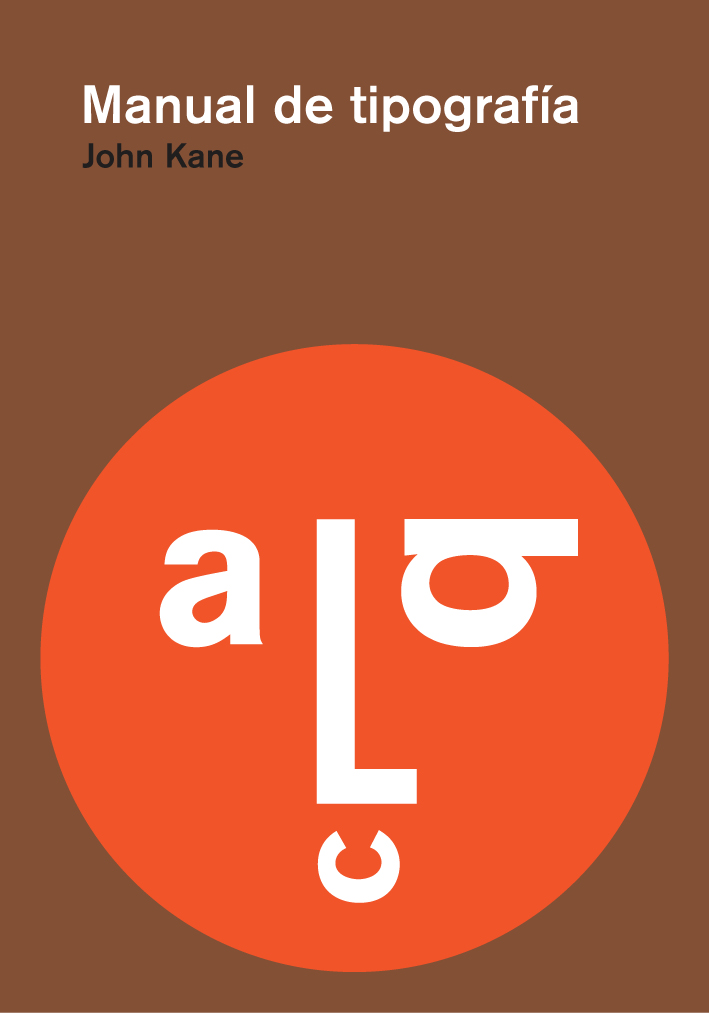
Manual de tipografía
Un libro de John Kane
Este libro constituye una práctica introducción a la tipografía donde se abordan sus principios básicos y sus distintas
aplicaciones. El autor analiza todo lo que el estudiante que
inicia sus estudios de diseño gráfico precisa conocer acerca de la tipografía: desde la clasificación de las diferentes tipografías a la disposición del texto en la página y el
funcionamiento de los sistemas de retículas. Además, incluye una breve historia de la tipografía, numerosos ejemplos que ilustran las cuestiones desarrolladas a lo largo del libro y una serie de ejercicios prácticos que sirven de ayuda al lector.
Índice de contenidos: Agradecimientos Presentación Conocimientos básicos Describir las partes de la letra La fuente Describir los tipos Medir la tipografía Comparar los tipos Desarrollo Una línea temporal Clasificación de las tipografías de texto Letras Comprender las formas de letras Mantener la altura de x Forma y contraforma Contraste Palabras y frases Reforzar el significado Crear oraciones, encontrar el sentido El español no es chino Texto El tracking: el kerning y el interletrado Composición de textos Textura No es lo mismo mecanografía que composición tipográfica El interlineado y la longitud de línea Un libro de muestras de tipo Indicar los párrafos Líneas viudas y huérfanas Destacar textos Titulares dentro del texto Alineaciones cruzadas Una organización sencilla Tipos de proporciones Ubicación del texto en la página Expresarse con jerarquías tipográficas Información tabulada Sistemas de retículas Introducción Un ejemplo Componentes de la retícula Una retícula sencilla Crear una retícula para texto e imágenes Conclusiones Apéndices y bibliografía Apéndice A: disposición de las letras en el teclado Macintosh Apéndice B: 20 tipos Selección de bibliografía Índice de términos |
Presentación: Diseñar es resolver problemas. El diseño gráfico consiste en resolver problemas creando signos. La tipografía es un conjunto de signos especialmente rico, porque consigue que el lenguaje sea visible. Manejar la tipografía de forma efectiva es esencial para un diseño gráfico efectivo. Dicho esto, puedo afirmar que este es un libro práctico. Durante más o menos los últimos veinte años que he dedicado a enseñar tipografía, he sido incapaz de encontrar un solo texto que les explicase con claridad a los estudiantes principiantes la compleja conjunción de mensaje, imagen e historia que conforma la tipografía. Algunos de los mejores textos sobre historia carecen de ejemplos suficientes; algunos de los mejores textos teóricos se dirigen más a los profesionales que a los novatos. Y no hay ningún texto que ofrezca a los estudiantes los datos fundamentales según una secuencia que refuerce los ejercicios básicos que se realizan en cualquier curso introductorio. Lo que pretendo con este libro es presentar los principios básicos y las aplicaciones tipográficas de un modo que refleje lo que ocurre en el aula, y corroborar esa información con una serie de ejercicios que consoliden los conocimientos adquiridos. Mi intención es acompañarte a ti, estudiante principiante de diseño gráfico, hasta el punto en el que puedas comprender y demostrar los principios básicos de la tipografía. Si el instinto es la suma del conocimiento y la experiencia, este libro constituye un intento de ampliar ambas cosas con el fin de reforzar tus propias intuiciones tipográficas. También debería señalar que este es un libro para autodidactas. Lo que yo sé sobre tipografía lo aprendí a base de lectura, práctica y observación. Fui lo bastante afortunado al leer a Emil Ruder en primer lugar. Y también lo fui por poder trabajar en Boston en una época en la que había docenas de profesionales de gran talento que estaban intentando resolver los mismos problemas a los que yo me enfrentaba cotidianamente, a medida que todos íbamos pasando desde la tipografía de plomo hacia la tipografía digital de nuestros Macs, pasando por la fase intermedia de la tipografía de fotocomposición. Lo que aprendí de todo este proceso fue la aplicación constante de la teoría a la práctica, el firme respeto hacia las letras y una búsqueda incesante de esos momentos en los que lo personal se unía —o por lo menos se acercaba— a lo platónico. Paul Rand escribió en una ocasión: 'La tipografía es un arte. La buena tipografía es Arte'. Y aquí radica el problema tanto de los profesores como de los alumnos. El oficio puede enseñarse. El arte está dentro de cada persona. Para muchos estudiantes que empiezan con la tipografía, el hecho de que no haya reglas seguras, ni exista un camino infalible para llegar al éxito, resulta frustrante. La dificultad pedagógica reside en que la tipografía es un sistema de principios basado en la experiencia, y esos principios siguen evolucionando a medida que evolucionan el lenguaje y los medios de comunicación. En innumerables ocasiones los estudiantes han preguntado: '¿Es esto correcto?', cuando de hecho no existe 'lo correcto' en tipografía. La cuestión que deberían plantearse es: '¿Funciona esto? ¿Es útil?' Los diseñadores utilizan la tipografía como reacción; como reacción a un mensaje, a un público, a un medio. La única forma de reconocer la tipografía que funciona bien es a través de una observación directa e informada. Hace falta tiempo, y hacen falta ensayos y errores para saber qué es lo que funciona, y para no preocuparse por lo que pueda ser 'correcto' o no. Cuando hayas terminado los ejercicios de este libro, deberías tener ya la experiencia suficiente como para poner a prueba tus propias ideas en relación con el uso de la tipografía. Al fin y al cabo, lo que cualquier diseñador aporta a un proyecto —la suma de lo que sabe y siente, su experiencia personal y única— es lo que garantiza que la variedad, la emoción y, ocasionalmente, la excelencia continuarán animando el diseño tipográfico. Este libro no trata sobre el estilo —una expresión característica de la actitud—, sino más bien sobre una forma clara y nítida de pensar y de hacer. El estilo pertenece al individuo; disfrutar pensando y haciendo es una sensación que todos pueden compartir. Las actitudes que han impulsado la mayor parte de las páginas que siguen son las mismas que han animado la mayor parte del arte en el siglo xx: El contenido dicta la forma. Más es menos. Dios está en los detalles. Estos tres dogmas identifican claramente el trabajo del tipógrafo: la expresión clara y apropiada del mensaje del autor, la economía de medios inteligente y un entendimiento profundo del oficio. La idea fundamental que subyace en este libro es el resultado de dos observaciones muy sencillas. En primer lugar, la tipografía es física. Hasta no hace mucho, cualquier formación en tipografía necesariamente comenzaba con la composición manual de tipos de metal. Sigue sin haber ningún modo mejor que este para comprender la absoluta fisicidad de la letra, su 'cosedad'. Cada día que pasa, sin embargo, resulta más imposible trabajar con tipos de metal. Para acercarse a la experiencia de manejar manualmente los tipos, se incluyen en este libro algunos ejercicios que exigen la representación cuidadosa de las letras. (He propuesto estos ejercicios sobre todo para los lectores que, como yo, carecen de las ventajas de una experiencia en las aulas. No se pretende que estos ejercicios sustituyan el trabajo con un buen profesor pero, desde luego, yo espero que puedan potenciar el aprendizaje también en ese caso). Estos ejercicios te ayudarán no sólo a afinar la coordinación entre tu mano y tu ojo, sino también a desarrollar cierta sensibilidad tipográfica. No puedes alcanzar esta sensibilidad solamente mirando y pensando. La única forma de valorar la realidad de la tipografía es interiorizarla. Para algunos de los ejercicios iniciales, la mejor técnica consiste en trabajar con una buena fotocopiadora. Además de proporcionar copias rápidas y claras, así como ampliaciones y reducciones razonablemente fiables, también te permite trabajar con las letras dentro de un marco, un eco débil pero audible de la fundición de moldes en un lingote de plomo. La segunda observación, sobre todo en términos tipográficos, es que la tipografía ha evolucionado a partir de la escritura manual. Si bien puede hacerse toda clase de cosas con la tipografía de un texto (en especial con un ordenador), tu trabajo logrará el mayor grado de integridad cuando lo que hagas refleje el mismo impulso que nos lleva a todos a ponernos a escribir: la comunicación efectiva, directa y útil. He adoptado la perspectiva, sobre todo en los ejercicios finales, de que las personas que usan este libro se mueven con familiaridad en el ámbito de los programas Adobe Illustrator y Quark Xpress o Adobe InDesign. También deberías disponer de por lo menos una fuente de cada una de las clasificaciones que se describen en las páginas 47-49; de hecho, no estaría mal que escogieses las diez tipografías que se destacan en la página 12. Estas tipografías ofrecen un fundamento sólido como una roca para cualquier clase de problemas relacionados con el diseño tipográfico que el futuro te pueda deparar. He utilizado numerosos ejemplos con el fin de demostrar los puntos que planteo, porque una de las cosas agradables de trabajar con tipografía es que se puede ver de forma inmediata si algo funciona o no (por esa misma razón, he tratado de reducir el texto a su mínima expresión). He diseñado prácticamente todos los ejemplos para que fuesen lo mas sencillos posible. Y esto por dos razones: en primer lugar, porque lo 'sencillo' es engañosamente difícil (y en el ámbito de la tipografía es, con frecuencia, lo deseable); y en segundo lugar, porque, como ya he dicho antes, este libro versa sobre la intención y el contenido, no sobre los efectos o el estilo. Finalmente, tal como sugiere el título, este libro solamente es un principio. Sus páginas describen, como máximo, una serie de pequeños pasos que conducen al desarrollo de una sensibilidad tipográfica bien fundamentada. Más allá de esto, tienes que observar a tu alrededor. Cada vez que veas una manifestación del lenguaje, estarás observando tipografía. Pon a prueba lo que haces en relación con lo que hacen otros, y aprende cómo articular las diferencias. Lleva contigo un cuaderno de bocetos, y anota en él todas tus observaciones. Incluye tus propios ejemplos. Y aprovecha cualquier oportunidad, por muy modesta que sea, para aplicar la tipografía sobre el papel. Espero que este libro te impulse a emprender una exploración constante de un oficio dinámico y exigente. Con suerte, estimulará un proceso en el cual la tipografía se convertirá en parte integral de tu vida profesional. |